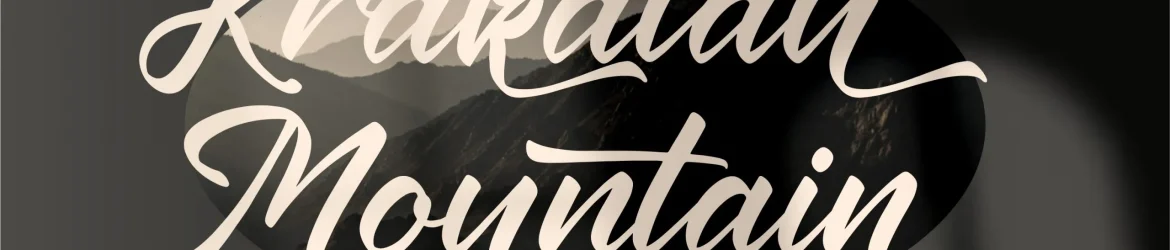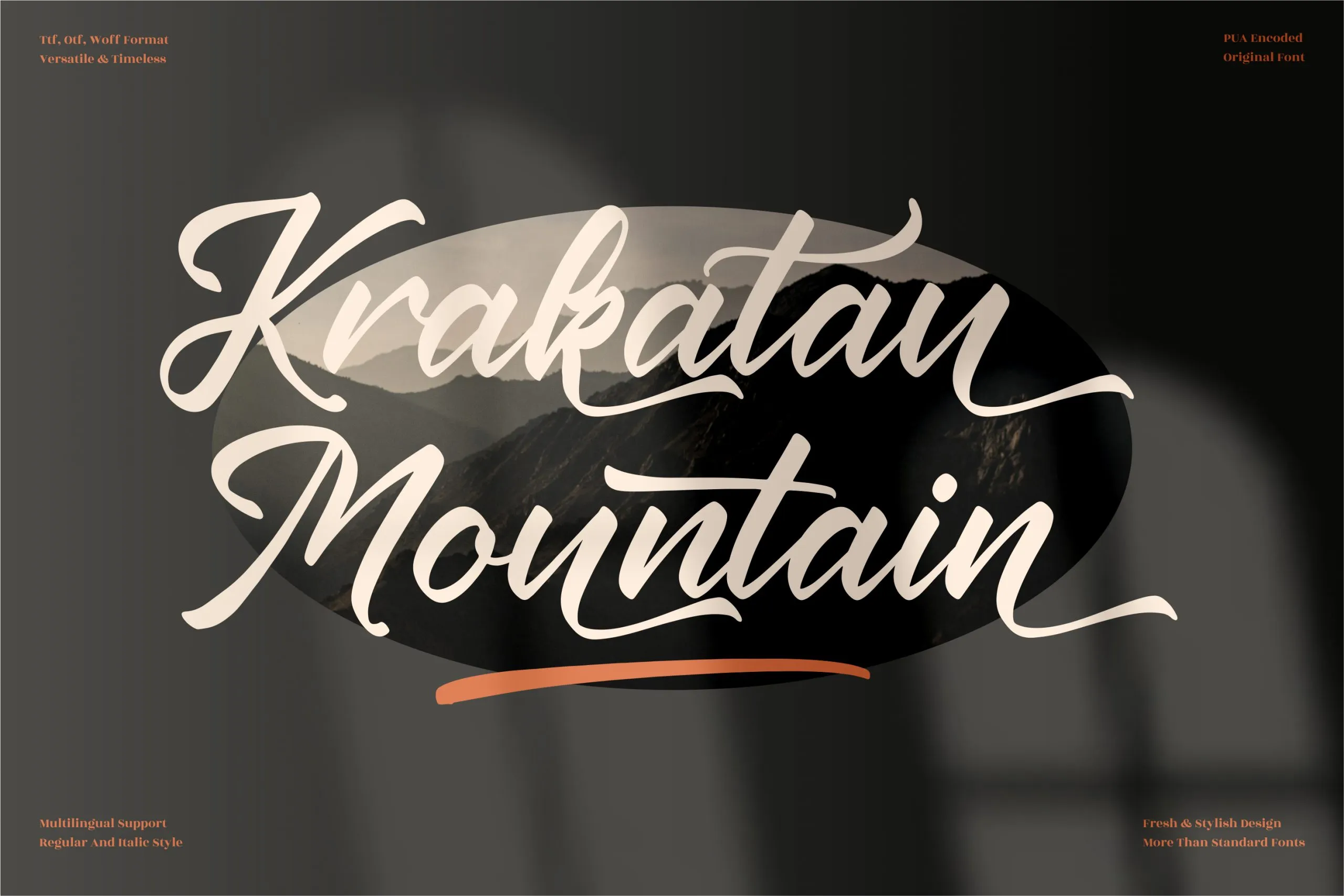
Krakatau Mountain Font
Esta é uma fonte de firma premium perfeita para qualquer projeto que valorize a sua marca. Perfeitamente adaptada para logos, criação de marcas, designs para itens domésticos, embalagens de produtos, chinelos, cartões de autógrafos, cartas de convite e cards de aniversário, capas de livros, etiquetas, fotos e até mesmo impressões digitais de eventos especiais. O Krakatau Mountain Font é a escolha perfeita para todos os seus projetos que desejam um sabor premium em sua identidade visual. Seja você uma marca ou designer, este fonte oferece aos usuários a habilidade de adicionar um toque singular à suas criações com seu giz exclusivo. Descubra por si mesmo a diferença que esse único clique pode fazer para seus projetos.